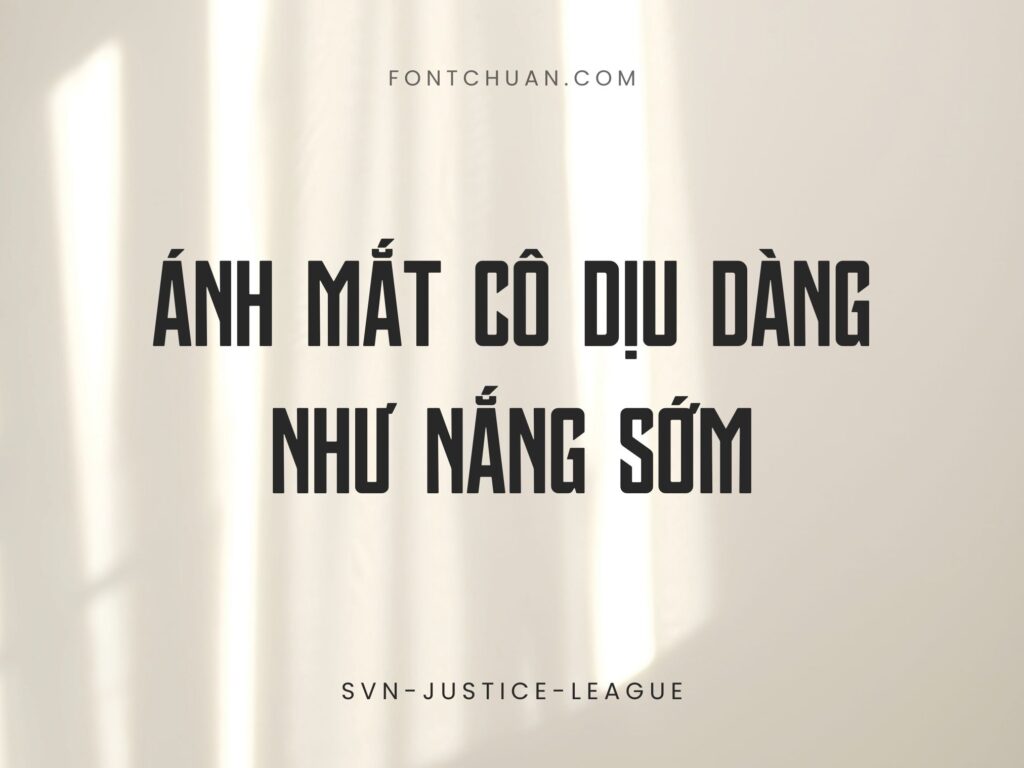
Font SVN Justice League Việt Hóa
Tác giả Font: Franco Fernandez
Font SVN Justice League là phiên bản Việt hóa của kiểu chữ Justice League, được thực hiện bởi STYLEno.1 Fonts. Justice League là một kiểu chữ display lấy cảm hứng từ logo của nhóm siêu anh hùng nổi tiếng cùng tên trong vũ trụ DC Comics. Font này mang phong cách mạnh mẽ và hiện đại, với các đường nét góc cạnh và đậm chất hành động, tạo nên sự nổi bật trong thiết kế. Font bao gồm các ký tự chữ hoa, chữ số và dấu câu, hỗ trợ đa ngôn ngữ. Với thiết kế đặc trưng, Justice League phù hợp cho nhiều mục đích sử dụng như thiết kế tiêu đề, logo, poster, bao bì sản phẩm và các ấn phẩm truyền thông liên quan đến chủ đề siêu anh hùng hoặc hành động.
SVN Justice League lý tưởng cho các dự án thiết kế yêu cầu sự mạnh mẽ và nổi bật, như thiết kế tiêu đề, logo thương hiệu và các ấn phẩm truyền thông. Các ngành nghề như quảng cáo, giáo dục và công nghệ có thể tận dụng font này để tạo điểm nhấn trong thiết kế. Ngoài ra, font cũng thích hợp cho các sự kiện như Tết, Giáng sinh, Halloween và các lễ hội khác.